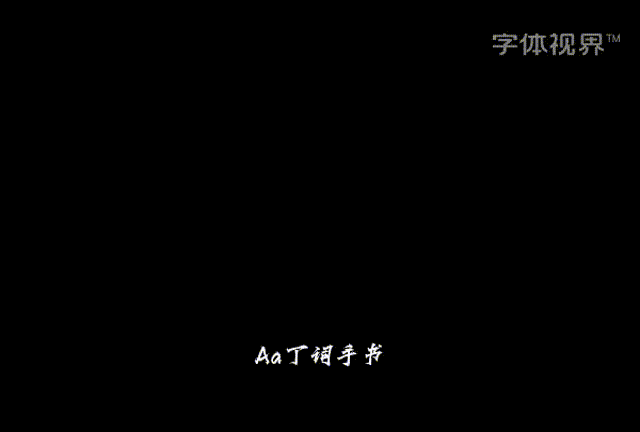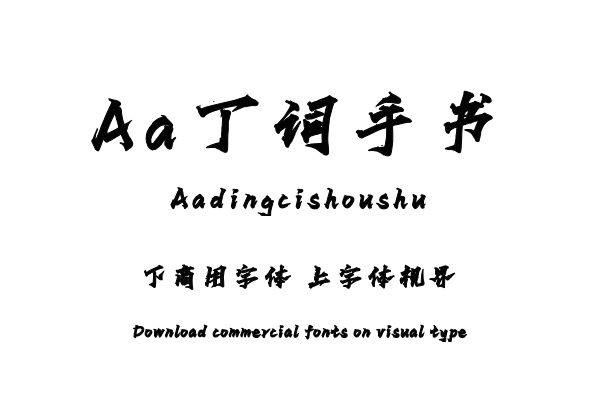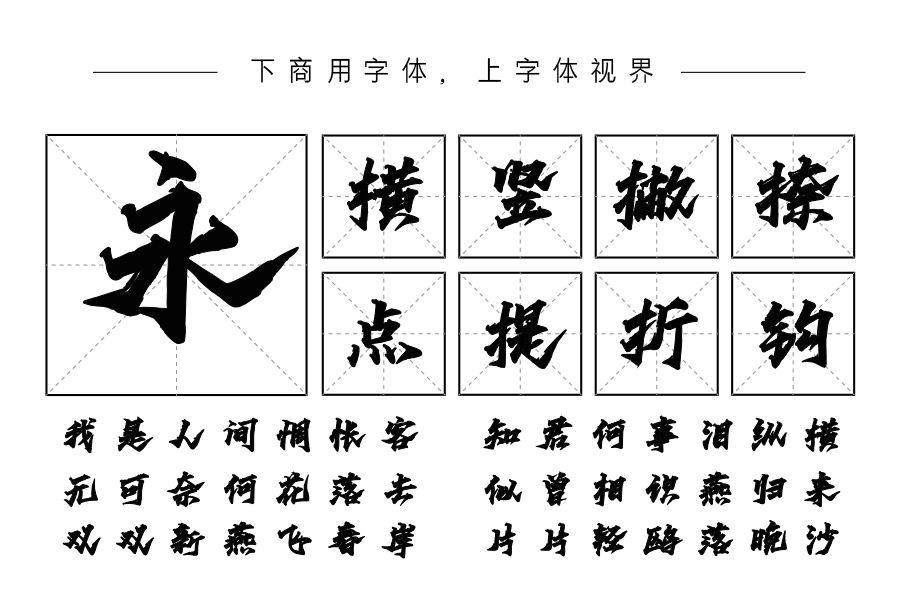
设计一款动势强劲的手写字库,满足市场对豪放手写字的多样化需求。 倾斜的笔形、弯曲而劲韧的竖笔与上挑的笔锋,使这款字体拥有了不同于传统书法字体的横排可能。购买须知:“下载服务费”与“字体VIP”所获得字体 仅用于个人非商用, 商用请联系付费授权。本字体为电脑用字,手机没有root权限不支持直接手机换字(手机如何root,请自行百度搜索教程)。购买前请先 了解清楚后再付款 ,字体为虚拟产品无法回收 一旦购买不支持退款。